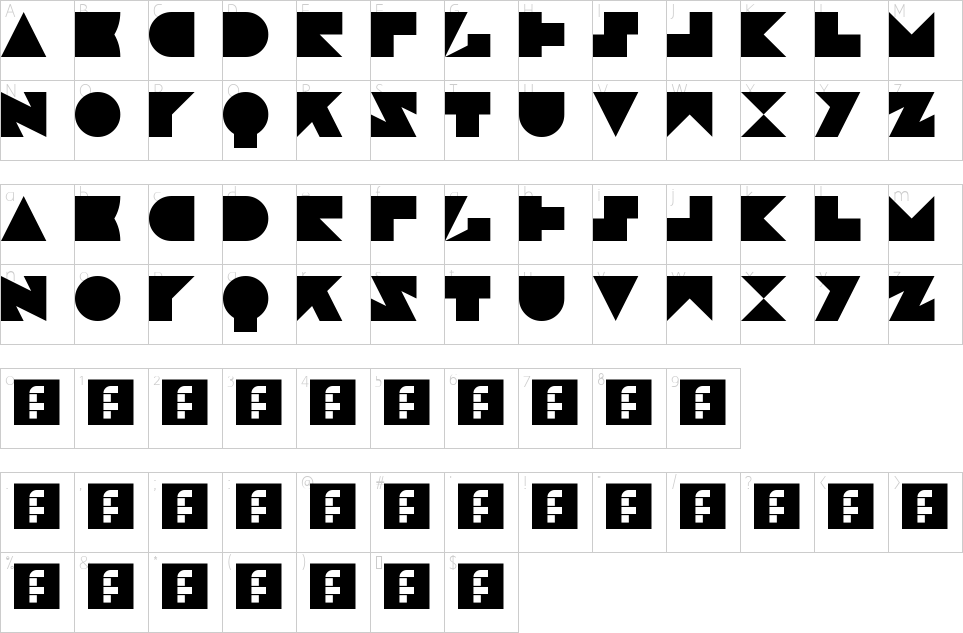
A fonte Jamstone é uma escolha perfeita para quem busca um equilíbrio entre simplicidade e elegância. Desenvolvida por Geronimo Fonts, esta fonte foi projetada para criar um estilo minimalista que se adapta bem tanto para textos legíveis quanto para desenhos gráficos. Com um design limpo e moderno, Jamstone é perfeito para aqueles que buscam uma fonte que ofereça uma ótima legibilidade e atende a um amplo leque de aplicações, desde editoriais até websites. Com seus 4,726 downloads, Jamstone é uma fonte gratuita de qualidade que merece ser explorada, seja para um projeto pessoal ou profissional. Download a Jamstone font e encontre a sua font perfeita para o seu projeto.